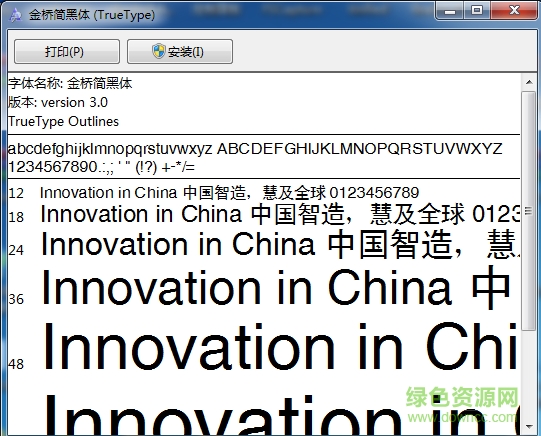
金桥简黑体
金桥简黑体字体是一款金桥黑体字,广告海报设计必备字体,大气简洁,而且金桥简黑体字体使用范围十分的广泛,可以在作品广告中经常看到一些这样的字体,需要的朋友赶紧来绿色资源网下载吧
随着社会的经济与文化的飞速发展,原有的一些基本字体已不能满足各种大众传媒的多方位、多层面的需求,这就要求设计人员在原有基本字体的基础上采取多种构思、多种形式和手法去创造丰富多彩又极富个性化的字体,用以补充有限的基本字体表现力度不足之缺憾。而这正需要每一个设计人员以规范和秩序为依托,在一定范围上去突破基本字体在外形、结构及笔形等形式上的严格束缚。为此,在不影响认读的前提之下,依据文字的内容和具体语境的允许之前题下,尽量挖掘设计者自身的知识积累,大胆开拓各方面的联想和想像空间,不断总结各种形式法则及其变化规律,不厌其烦地去推敲所需表达文字的精神实质,从而达到以鲜明的艺术表现形式去增强作品自身的艺术感染力。特别是创意字体的设计,要在整体风格上勇于突破基本字体的固定模式。设计者更要在醒目、独特、灵动、意趣等夺人耳目的意态上发挥更多的聪明才智及潜能。总之,语言的形式重在“音”,文字的形式重在“形”,而二者共同表达的是“义”,音美以动听、形美以悦目、意美以传情,如何以形义之美而启动视听、激发意向正是字体设计在视觉传达中的重要意义之所在。
金桥简黑体是一款黑体字体,黑体字体又称方体或等线体,没有衬线装饰,字形端庄,笔画横平竖直,笔迹全部一样粗细。